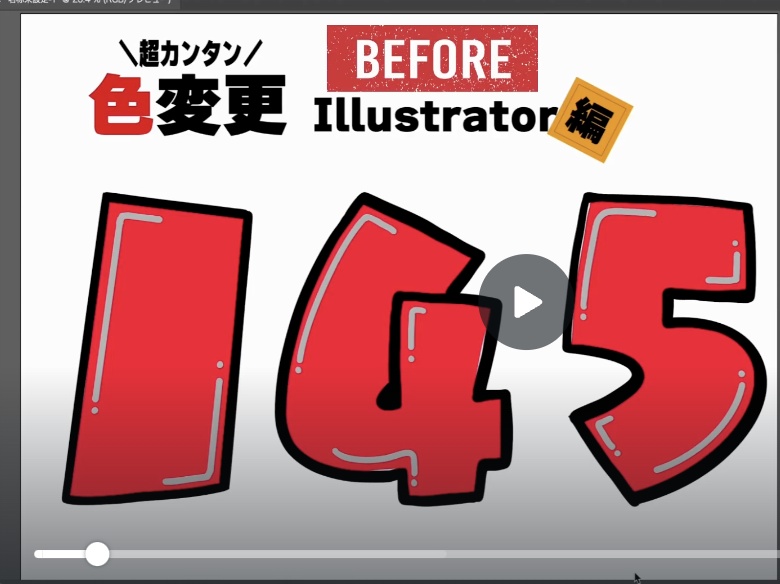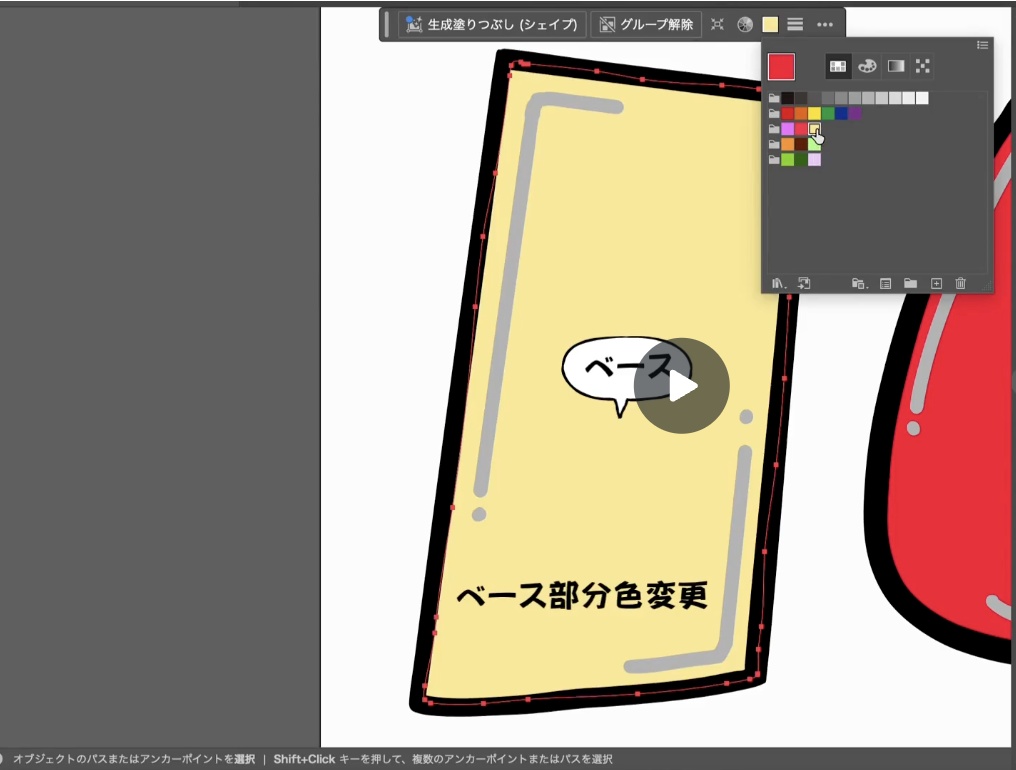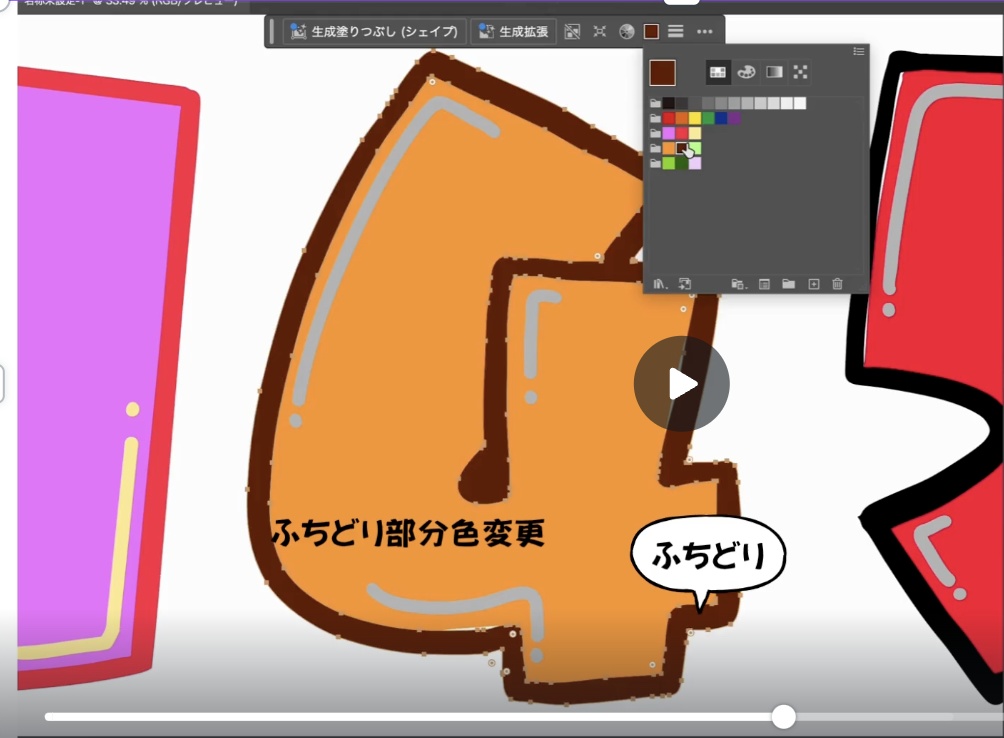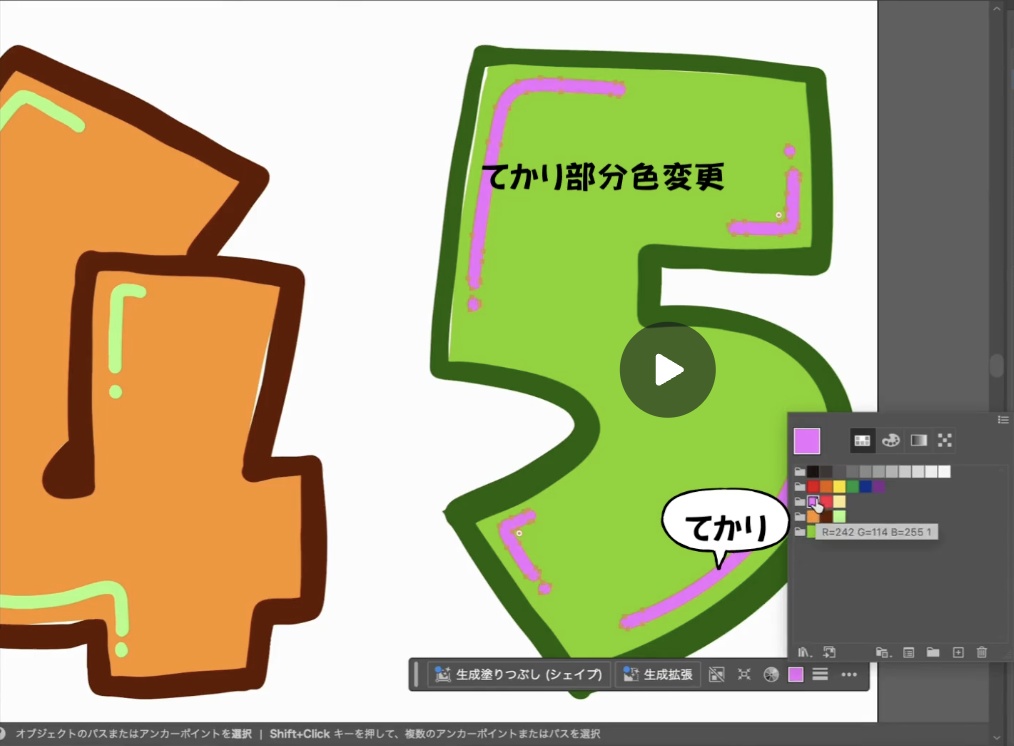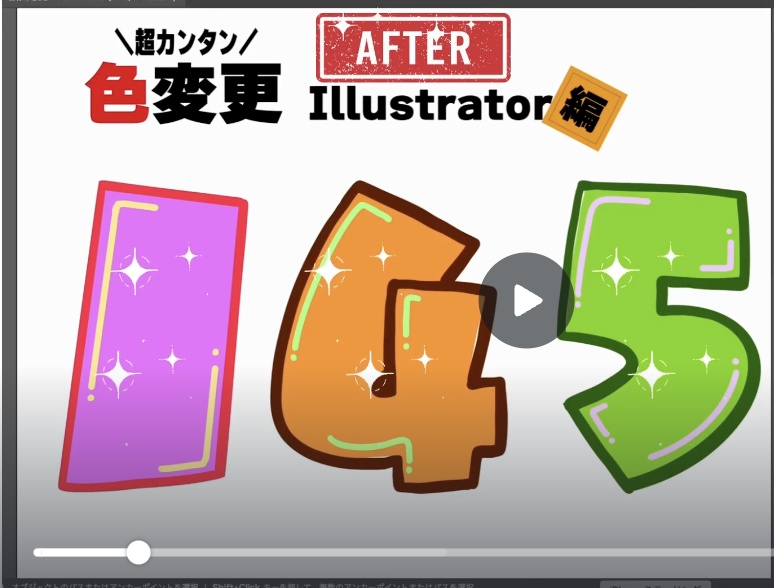
君乃フォント〜Numbers〜kimino-font-Numbers
✨ 君乃フォント – 手書き数字フォント ✨ 温かみのある手描きの数字フォントです。 Procreateで一つ一つ丁寧に描き、Illustratorでレイヤーごとに加工しました。 赤ベース・黒ふちどり・白てかりの3レイヤー構造になっており、 購入後は色を自由に変更できます🎨 ・0〜9、記号(, / 円)などを収録 ・各パーツはSVGで収録、Illustratorで色変更可能 ・Canvaなどでも使いやすい ⸻ 📝今後の予定 ・「残暑お見舞い申し上げます」 ・「おつかれさま」 ・「ほんのきもちです」 など、手書きメッセージフォントも発売予定です! ⸻ 💡個人・商用利用OK 🥹使っていただいたことを知らせていただけると、とっても喜びます❣️